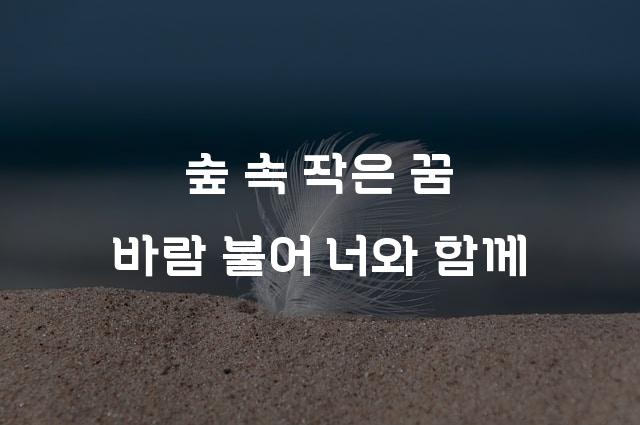
길벗체 BI는 비온뒤무지개재단에서 제작한 고딕 스타일의 폰트로, 장식적 요소가 가미된 독특한 디자인이 특징입니다. 강한 인상과 함께 세련된 느낌을 제공합니다.
길벗체 BI은(는)
기본 고딕, 굵은 고딕, 장식 스타일, 단단함, 별모양/패턴 계열의 생김새를 가지고 있으며
로고 디자인, 브랜딩 등에서 자주 활용되며, 효과적인 메시지 전달에 적합합니다.
이 폰트는 광고/마케팅, 크리에이티브 분야에 잘 어울리며,
창의적인, 전문적인 느낌을 담고 있는 것이 특징입니다.